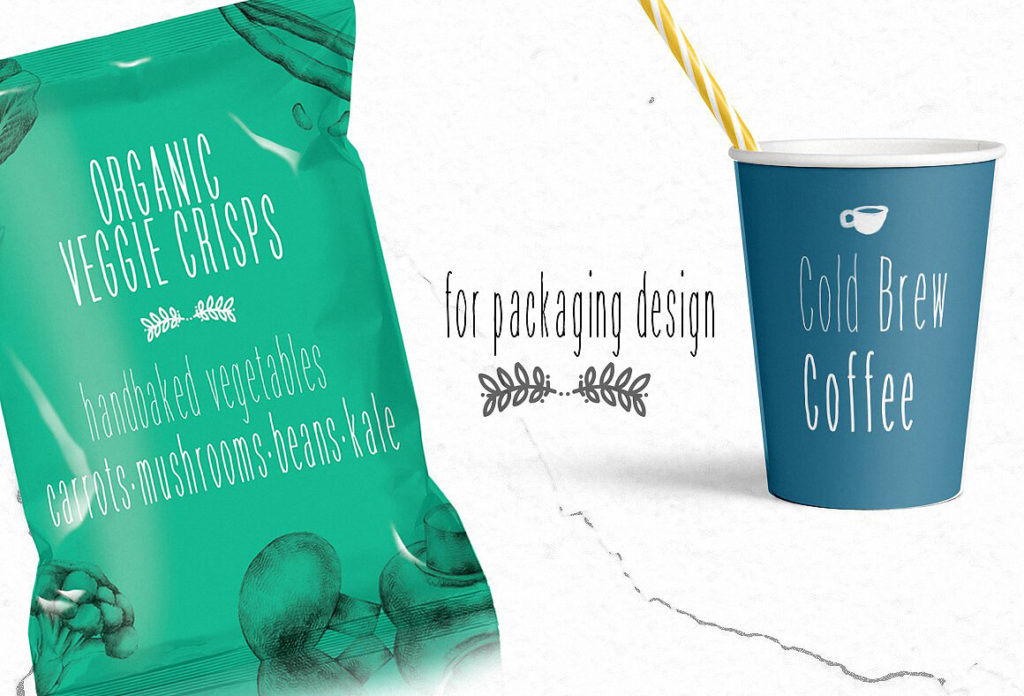
это элегантный рукописный гротеск (handwritten sans-serif), созданный дизайнером Константиной Лукой (Konstantina Louka). Это мультиязычный шрифт, который гармонично объединяет латиницу, кириллицу и греческий алфавит в едином стиле. Характеризуется плавными, естественными линиями, имитирующими почерк, при этом сохраняя высокую читаемость. Шрифт доступен в нескольких начертаниях (Thin, Normal, Heavy) и идеально подходит для проектов, требующих дружелюбного, но современного подхода. Вы можете **скачать бесплатно** кириллическую версию шрифта на этой странице